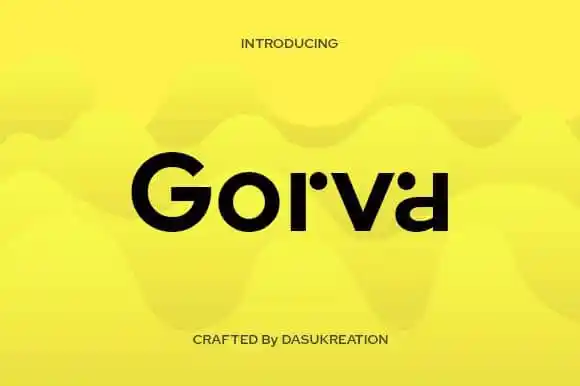
Gorva Sans Serif Font – Download Grátis
Agora está disponível a Gorva Sans Serif Font para você transformar sua identidade visual de maneiras modernas e vintage ao mesmo tempo. Nesse estilo geometrico e minimalista, essa nova fonte combina elegância clássica com uma aparência fresca e contemporânea. A Gorva é perfeita para criações em várias formas, desde camisetas até adesivos de porta-olhar, promovendo designs que destacam-se. Ela também será a escolha ideal para qualquer projeto onde você deseja um estilo moderno e original, sem perder seu visual vintage favorito. Composta por 99designs, essa fonte é uma excelente opção para designer gráficos buscando novas maneiras de personalizar suas criações.